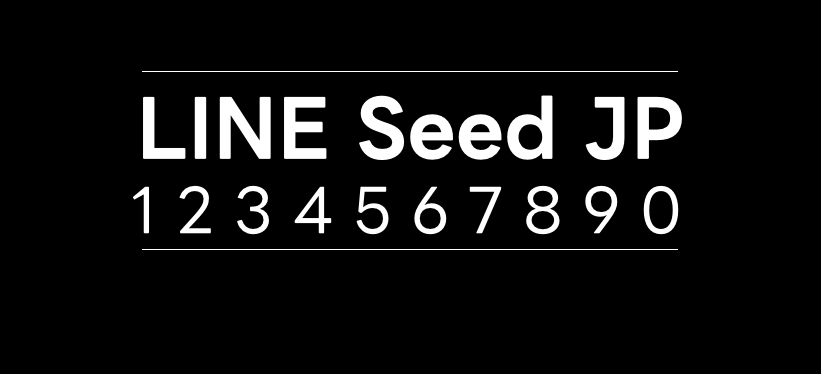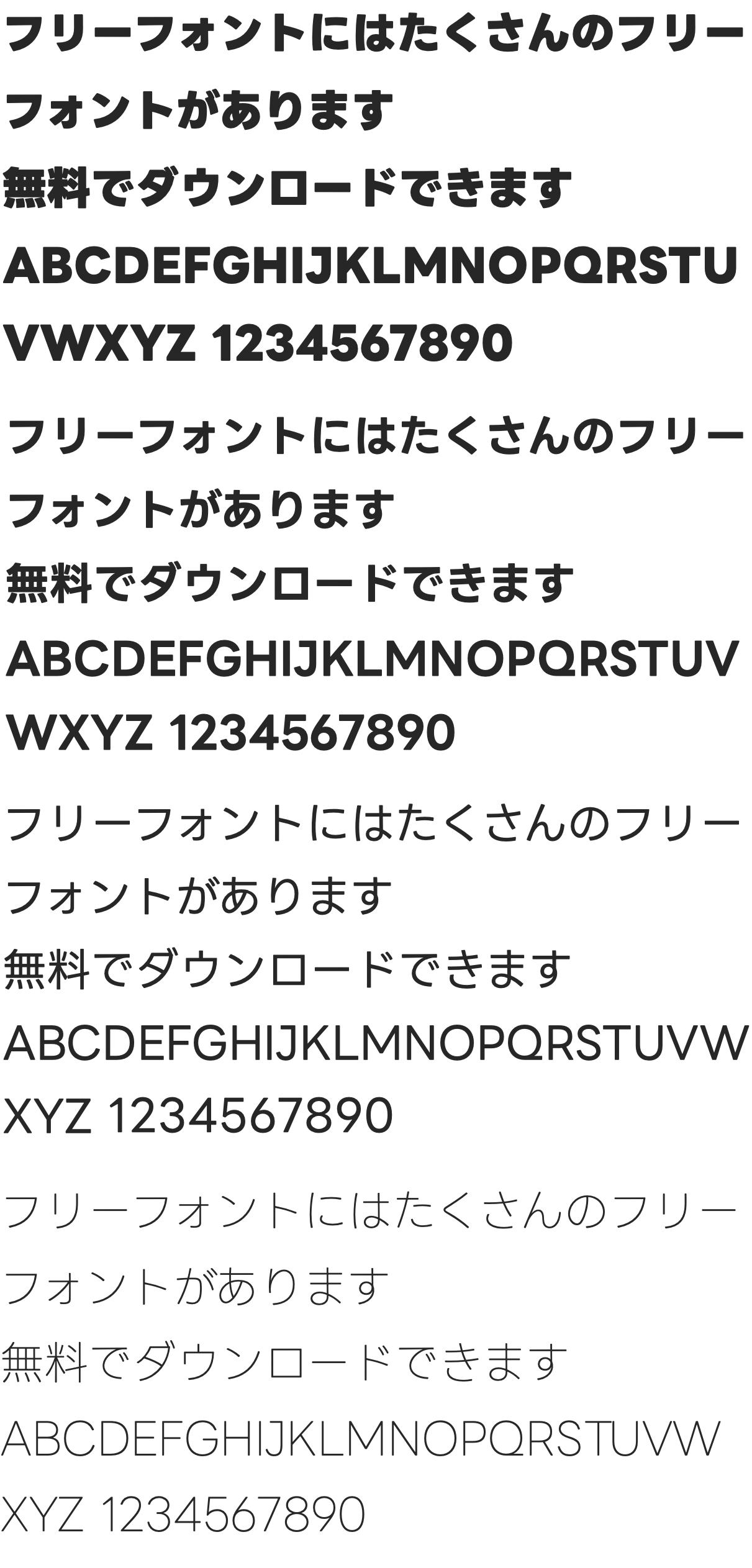
LINE Seed Sans JP
LINE Seed Sans JP是LINE Seed字体家族的日文版本。2022年10月日本互联网巨头LINE发布了其企业字体LINE Seed。由LINE自家设计团队、日本的Fontworks、英国的Dalton Maag、韩国的Fontrix、泰国的Cadson Demak联合开发。覆盖日、韩、英、泰四语言的常用文字。设计团队在 4 语言的协调感上花了非常多的工夫。